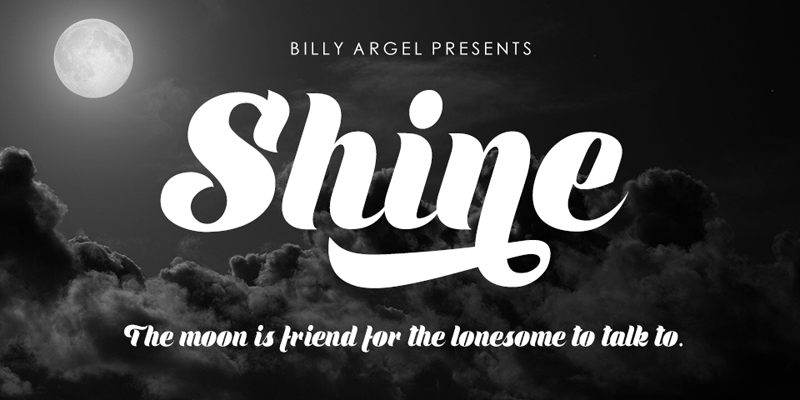
Esta fonte “Shine Script Font” é ideal para criar designs emocionantes que chamem a atenção dos seus seguidores. Conhecida por sua delicadeza e elegância, ela se torna um complemento perfeito para qualquer projeto visual que deseja destacar-se em uma maneira única. Desenvolvida pelo designer Billy Argel, essa fonte foi criada com um coração especial para aqueles que desejam dar vida a mensagens de forma linda e reconhecível. Se você busca personalizar suas páginas web, criação de logotipos ou qualquer projeto gráfico em geral, “Shine Script Font” oferece uma maneira de fazer isso ainda melhor. E se você está buscando usar essa fonte para fins comerciais, Billy Argel está disponível para fornecer as licenças necessárias e também a versão completa da fonte. Não hesite em entrar em contato com ele através do endereço  ou visitar sua página oficial no site www.billyargel.com.
Designer: Billy Argel